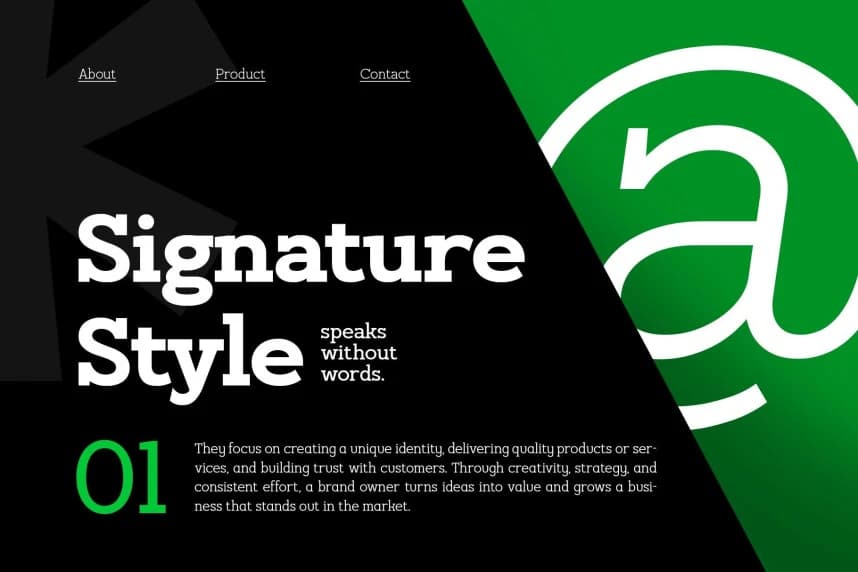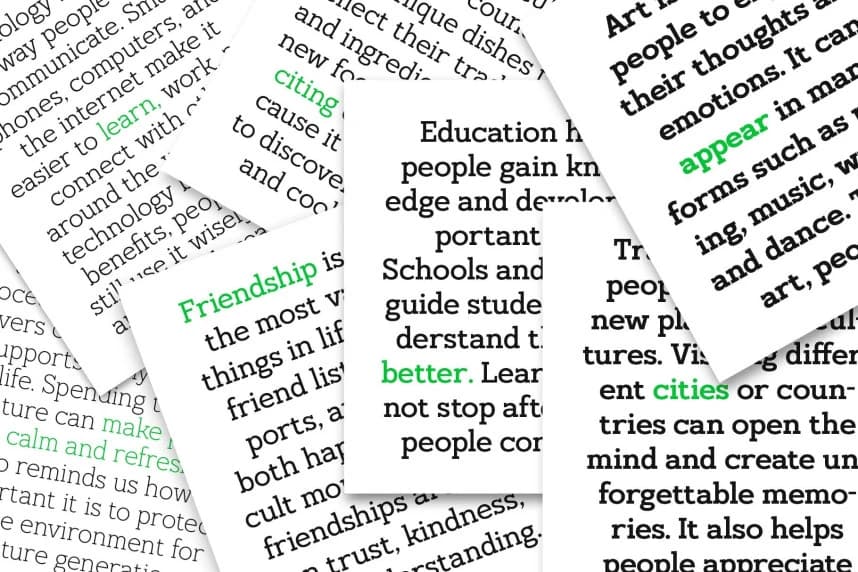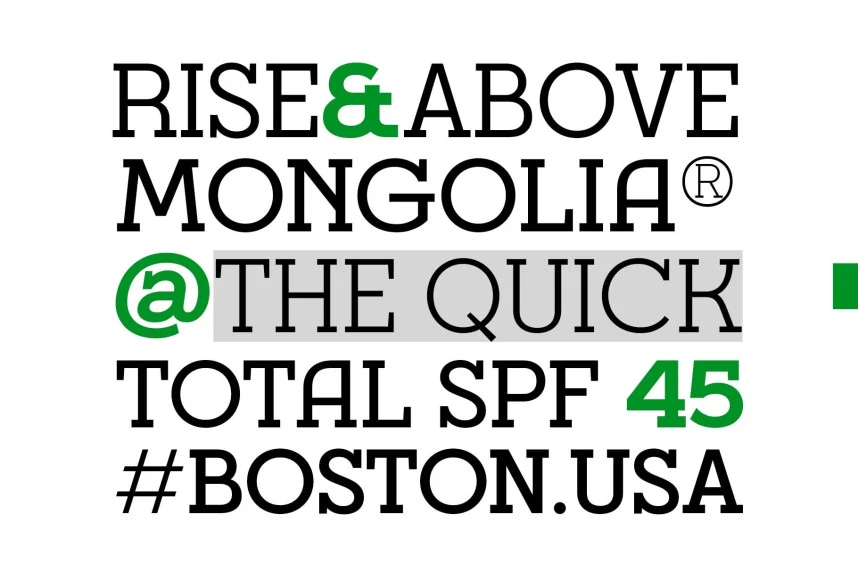
Hugells Font
Hugells Font, 7 ağırlıkta bulunan modern bir slab serif tip ailesidir ve herhangi bir tasarımda güçlü, zarif bir varlık sunacak şekilde tasarlanmıştır. Kalın seriflerle, dengeli oranlarla ve temiz yapıya sahip olan Hugells, kendine güvenen ve profesyonel bir ton yaratır—hem dijital hem de baskı uygu
Hugells Font, 7 ağırlıkta mevcut olan modern bir blokserif tip ailesidir; herhangi bir tasarımda güçlü ve zarif bir varlık sunacak şekilde tasarlandı. Kalın serifleri, dengeli oranları ve temiz yapısıyla Hugells güven veren ve profesyonel bir ton oluşturur—hem dijital hem de baskı uygulamaları için mükemmel.